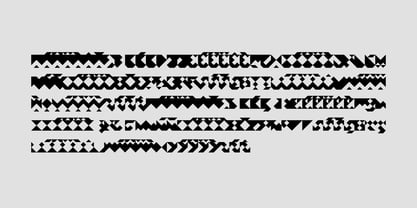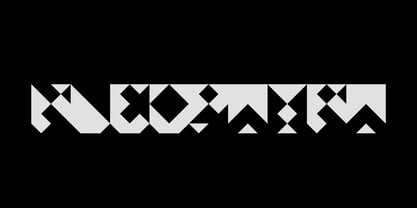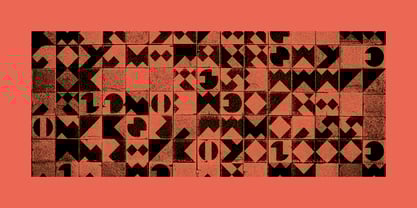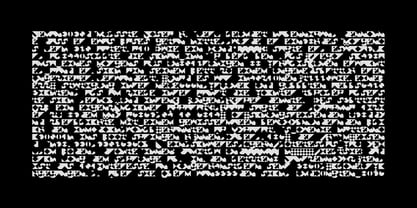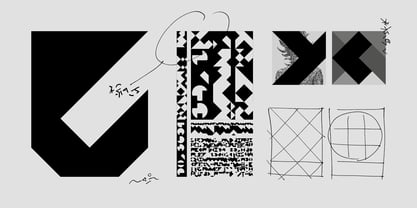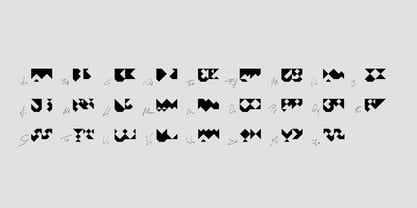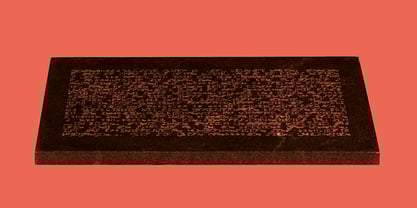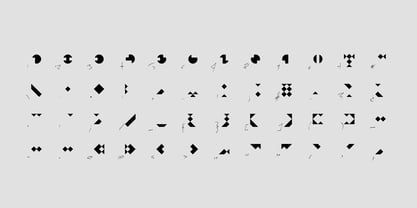
Kleopatra
by Luis Rutz
The Kleopatra Font Family was designed by Luis Rutz and published by Luis Rutz. Kleopatra contains 1 styles.
Futuristische Zeichen aus einer anderen Zeit. Hervorgebracht aus dem Sand von Memphis, 18 Kilometer südlich von Kairo. Gesammelt und rekonstruiert von deutschen Architekten, treu einer kompromisslosen Geometrie, die jemanden zu repräsentieren scheint, der sehr viel moderner ist.
About Luis Rutz
Deutscher Designer, lebt und arbeitet in München, Berlin und Paris. Hauptdisziplinen: Typografie, Schriftgestaltung und visuelle Systeme. Master-Alumnus der Bauhaus-Universität Weimar. Aktiv in den Bereichen Architektur, Kunst, Luxury und Fashion. Ziel ist visuelle Prägnanz, keine leeren Phrasen. Dem klassischen Ansatz verpflichtet, um neue, zukunftsorientierte Bilder zu schaffen.